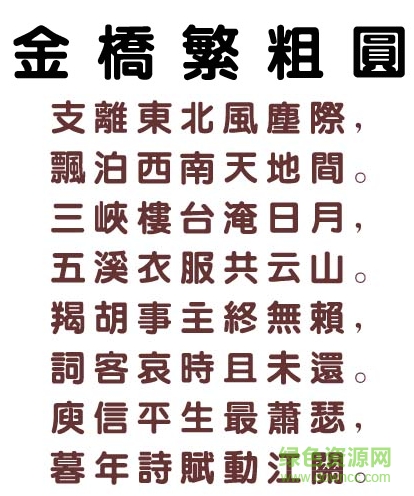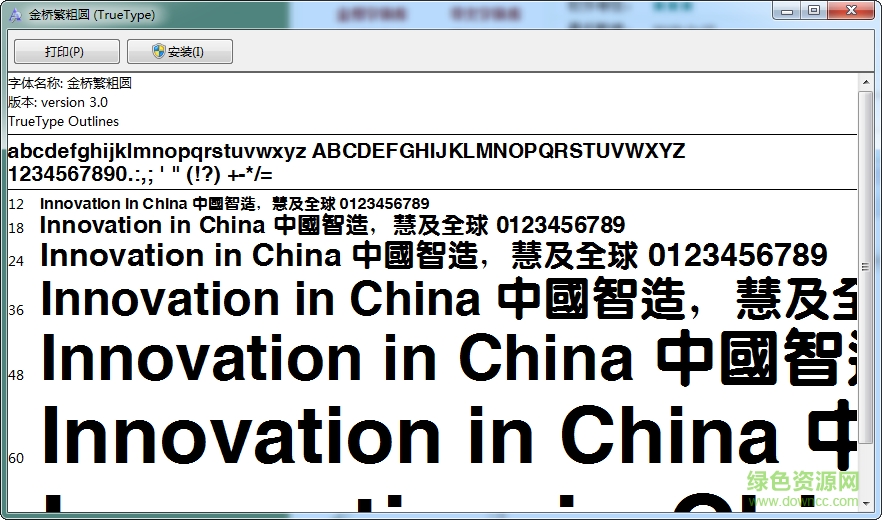
金橋繁粗圓是一款筆畫(huà)較粗,并且腳邊是圓形的簡(jiǎn)體字體,不論是廣告設(shè)計(jì),還是藝術(shù)創(chuàng)作中,都經(jīng)常用到。而且非常的具有觀賞價(jià)值,十分的大氣好看,喜歡這個(gè)字體的趕快來(lái)綠色資源網(wǎng)下載體驗(yàn)吧!